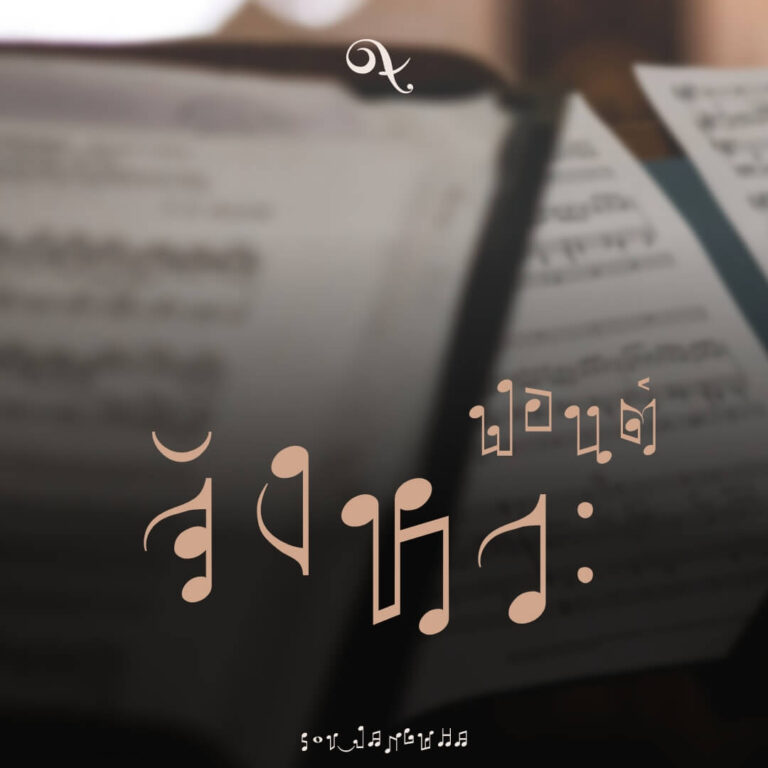
จังหวะ (SOV_JangWha)
ฟอนต์จังหวะ ตัวปรกติโน้ตจะโดดเด้งหน่อย เพื่อความครึกครื้น กด bold จะวางบนบรรทัด 5 เส้น เรียงเรียบๆ แต่ก็มีการเปลี่ยนโน้ต (เปลี่ยน glyph) เป็นจังหวะๆ (84) ถ้าเอามาพิมพ์ยาวๆ แนะนำให้เติมสัญลักษณ์ทางดนตรี จะดูสนุกขึ้น (ลองจิ้มๆ ดูว่าตัวไหนอยู่อักษรอะไร)